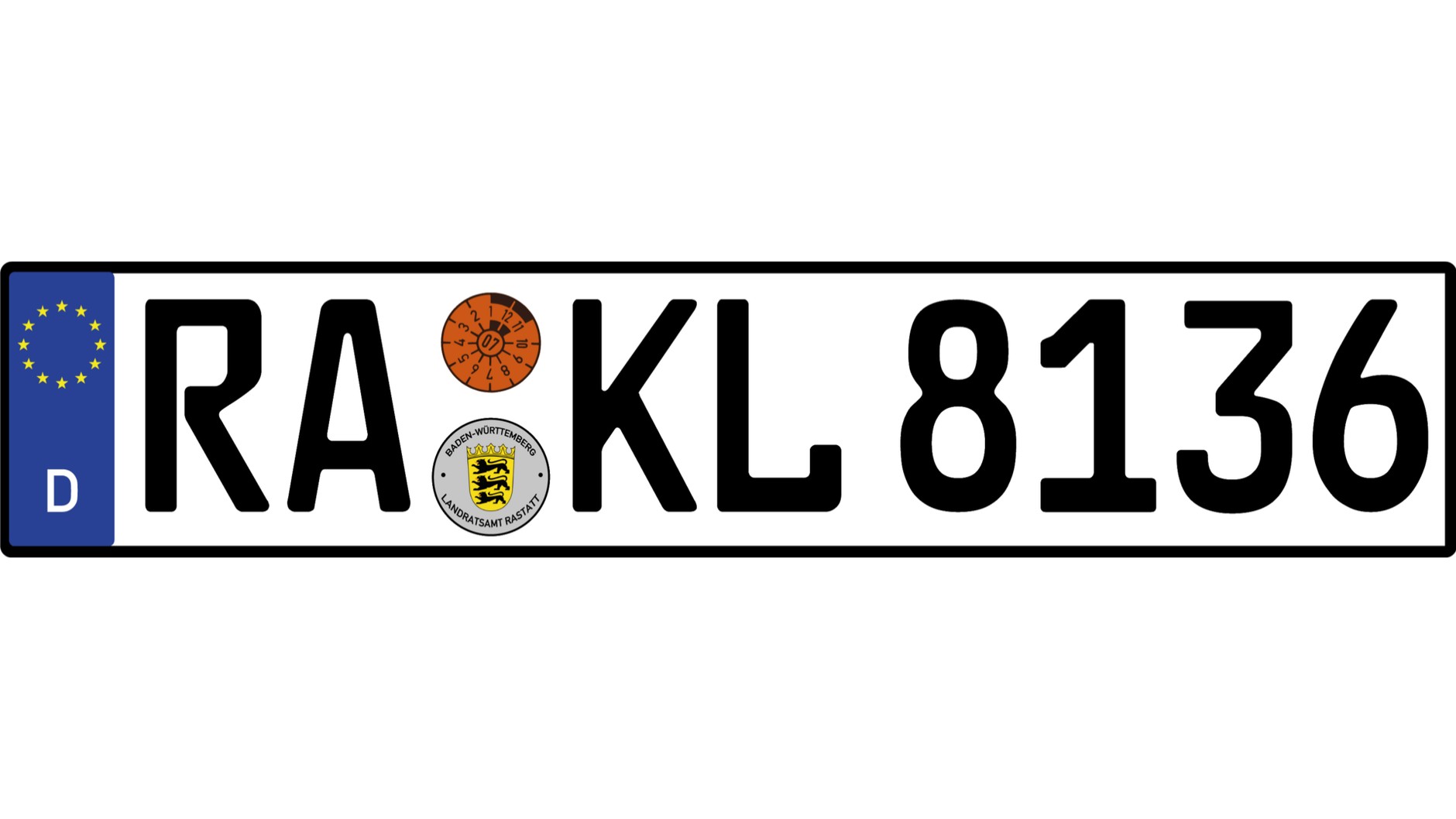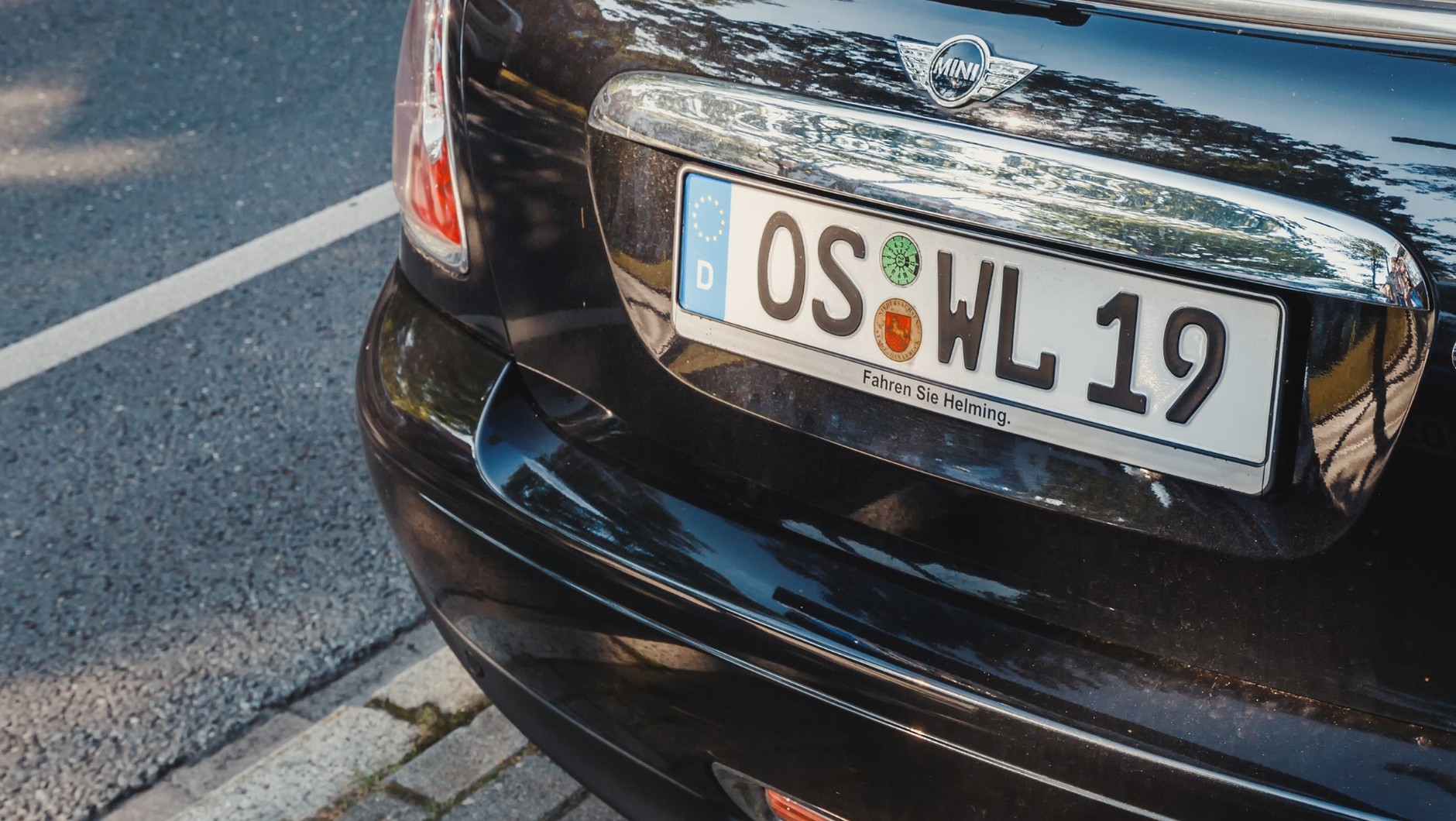
Przez nich Niemcy musieli zmienić tablice rejestracyjne. Dziś używają ich nawet w Afryce
Jeżdżąc po drogach w Niemczech, można natknąć się auta z charakterystycznymi tablicami rejestracyjnymi o specjalnie dobranej czcionce. Fachowo nazywa się ona Fälschungserschwerende Schrift (w skrócie FE-Schrift). Jednak nie zawsze tak było.
Dlaczego Niemcy zmienili czcionkę tablic rejestracyjnych na FE-Schrift?
Po zakończeniu II wojny światowej to czcionka DIN 1451 była szeroko używana m.in. w transporcie i administracji. Głównie ze względu na swoją prostotę i czytelność. Jednak w latach 70. pojawił się poważny problem.
To wtedy radykalne bojówki Frakcji Czerwonej Armii (RAF) kradły auta i w łatwy sposób przemalowywały oznaczenia na tablicach rejestracyjnych. Samochody były później wykorzystywane w działalności terrorystycznej. Ówczesny projekt był tak prosty, że zmiana litery "P" na "R" lub "L" na "E" nie sprawiała żadnych trudności.
Czym charakteryzuje się czcionka tablic rejestracyjnych FE-Schrift?
Przeciwdziałać temu miała nowa czcionka, która została zaprojektowana przez niemieckiego typografa Karla Georga Hoefera na zlecenie Federalnego Instytutu Dróg. Unikalne cechy FE-Schrift , takie jak stała szerokość znaków (każda litera i cyfra zajmuje dokładnie tyle samo miejsca w poziomie), mają na celu utrudnienie modyfikacji i poprawę czytelności.
Współczesne tablice rejestracyjne z Niemiec, zapisane FE-Schrift
Jednak nie od razu nowy krój czcionki został wprowadzony w Niemczech. FE-Schrift zaczęto stosować w niektórych krajach związkowych Niemiec już w 1994 r., a na terenie całych Niemiec od 1995 r. W 2000 r. całkowicie wyeliminowano ustawowo starsze wzory tablic rejestracyjnych.
Ze względu na trudności w podrobieniu czcionki została ona przyjęta przez inne kraje. Obecnie można spotkać ją m.in. na tablicach rejestracyjnych m.in. Urugwaju, Malty i Tanzanii.